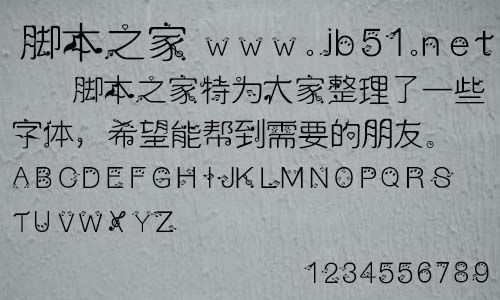
逐浪音樂符號(hào)歌譜體是一款中文藝術(shù)字體,這款字體的筆觸較為纖細(xì),在每一個(gè)字體中都點(diǎn)綴著音樂符號(hào)的裝飾,適合應(yīng)用于藝術(shù)設(shè)計(jì)、平面宣傳設(shè)計(jì),網(wǎng)頁(yè)設(shè)計(jì),書法字帖等領(lǐng)域,需要的朋友可以前來本站下載,